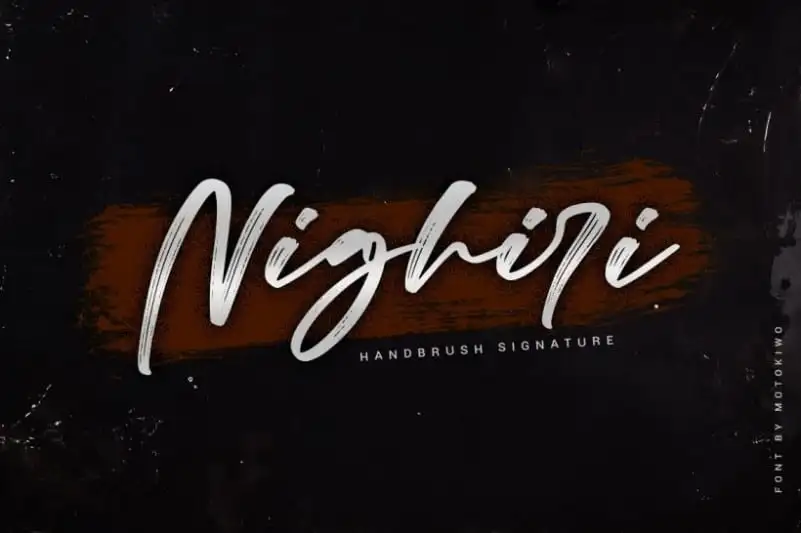
Nighiri Brush Font – Download Grátis
Nighiri Brush Font é uma elegante escolha para designers que desejam dar um toque autêntico e artesanal a seus projetos digitais. Trabalha perfeitamente se você combiná-lo com praticamente qualquer tipo de sans serif, conferindo ao seu design uma sensação de mão dura cunhada. Este tipo de letra foi criado e compartilhado por Motokiwo e tem um charme sofisticado que faz dele um favorito para projetos variados. Ideal para aplicar em postais, logotipos, headlines, citações, marcações de casamento, branding, moda ou qualquer outro projeto que você esteja planejando. Nighiri é recomendado por sua versatilidade e elegância, se tornando uma excelente opção tanto para projetos com grande destaque quanto para textos mais discretos. É uma escolha perfeita para aqueles buscando um toque único e sofisticado em suas criações digitais.